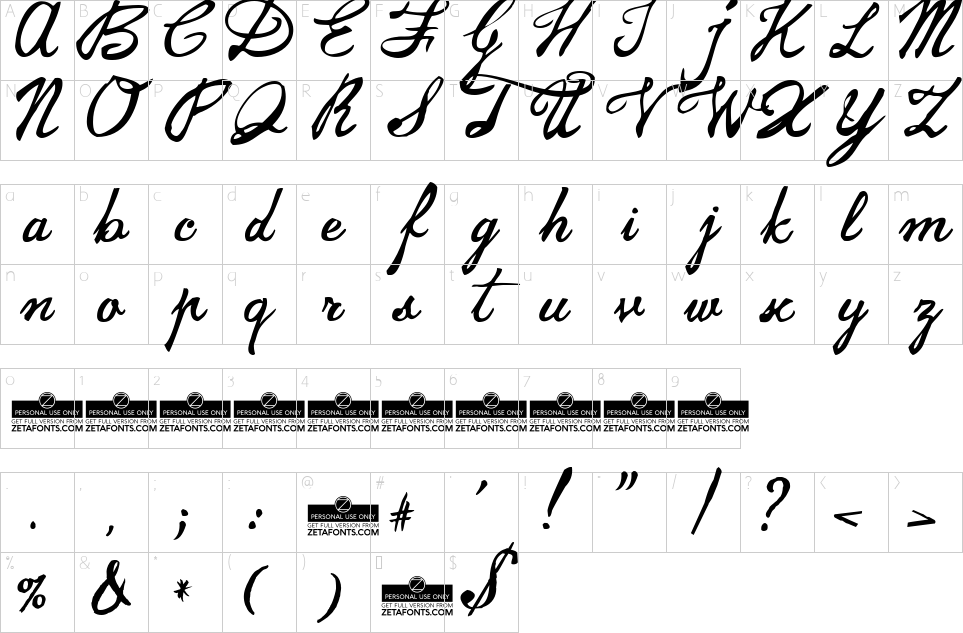
Jam Script Font | 1001 Free Fonts – Fonte Grátis
A fonte Jam Script é uma graciosamente simples e versátil fonte criada por Zetafonts, disponível tanto para Windows quanto para Mac. Ela é perfeita para criar um estilo casual e despojado em sua próxima criação visual. Com sua tipografia leve e agradável aos olhos, Jam Script é uma escolha ideal para headlines e pequenos tamanhos de texto, garantindo que seu design seja atraente e eficaz. Com downloads de 18.261 vezes, Jam Script já se tornou um recurso popular entre os criativos que procuram um estilo fresco para seus projetos. Se você está buscando uma fonte que combine elegância com simplicidade, Jam Script é a escolha perfeita para você.